Красные панды очень маленькие и больше похожи на кошек, чем на медведей, они питаются бамбуковыми стеблями и издают очень милые звуки. Но из их меха получаются красивые шапки, а на месте лесов, в которых они обитают, сейчас строят дороги, поэтому в дикой природе осталось меньше 10 000 красных панд. Всё это рассказал дизайнер Андрей Гродзь в своём проекте, где для лозунгов и тегов использовал Druk Wide.
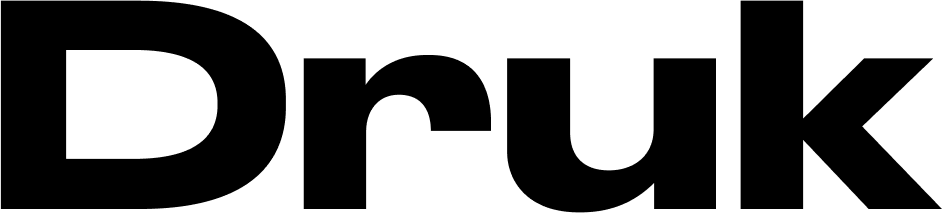
Druk Бёртона Хасиба был задуман как коллекция противоположностей, в которую вошли очень узкие, очень широкие и очень насыщенные начертания (от Medium до Super). При этом в коллекции нет начертаний нормальной ширины и начертаний тоньше полужирного. Кириллицу Druk нарисовали в CSTM Fonts.